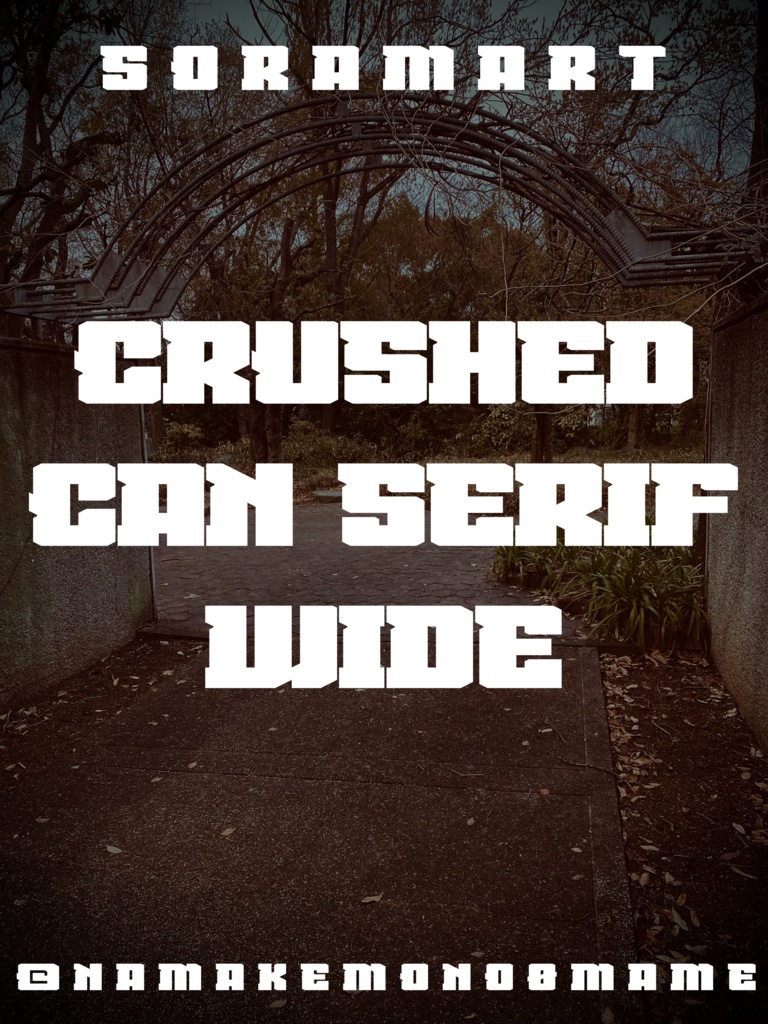
そらマートフォントデータ”Crushed Can Serif Wide”Digital2,500 JPY加入购物车Buy a GiftAbout Giftつぶれた空き缶から着想を得たハード太字フォント…を更に幅広化した "Crushed Can Serif Wide" です。 「TrueTypeフォントファイル」という形式です。 ダウンロードした後、Zipファイル内のデータをインストールしてお使いください。 このフォントは商用利用可となっております。 お客様の制作・創作活動のお役に立てれば幸いです。 ※使用上の注意事項などは、添付のReadmeをお読みください。そらマートVisit FANBOX!Fontsフォントデータ”RANMMA Drive”そらマート0 JPYFontsフォントデータ”Dandy Laser Max”そらマート2,500 JPYFontsフォントデータ”Dandy Laser”そらマート2,500 JPYFontsフォントデータ”Bubblegum Beat”そらマート2,500 JPYFontsフォントデータ”Caltrop Serif LLL”そらマート2,500 JPYFontsフォントデータ”Caltrop Serif LL”そらマート2,500 JPYFontsフォントデータ”Caltrop Serif”そらマート2,500 JPYFontsフォントデータ”Tonik Crate Super Long”そらマート2,500 JPYFontsフォントデータ”Dot Eat Bug Acid”そらマート2,500 JPYFontsフォントデータ”Dot Eat Bug Mild”そらマート2,500 JPYFontsフォントデータ”Dot Eat Bug”そらマート2,500 JPYFontsフォントデータ”Solid Voltage Strike”そらマート2,500 JPYFontsフォントデータ”Solid Voltage”そらマート2,500 JPYFontsフォントデータ”Henge Edge Rock”そらマート2,500 JPYFontsフォントデータ”Henge Edge Tall”そらマート0 JPYFontsフォントデータ”Henge Edge”そらマート0 JPYFontsフォントデータ”Chisel Stroke Wide”そらマート2,500 JPYFontsフォントデータ”Chisel Stroke”そらマート2,500 JPYFontsフォントデータ”Crushed Can Serif Empty”そらマート2,500 JPYFontsフォントデータ”Crushed Can Serif”そらマート2,500 JPY查看更多